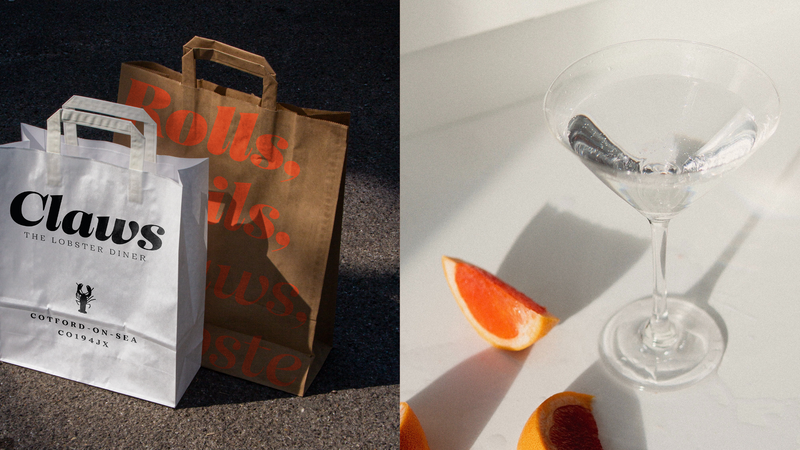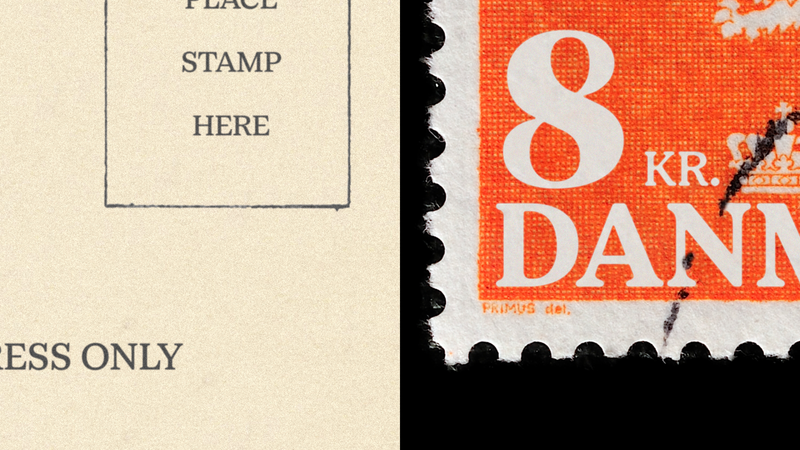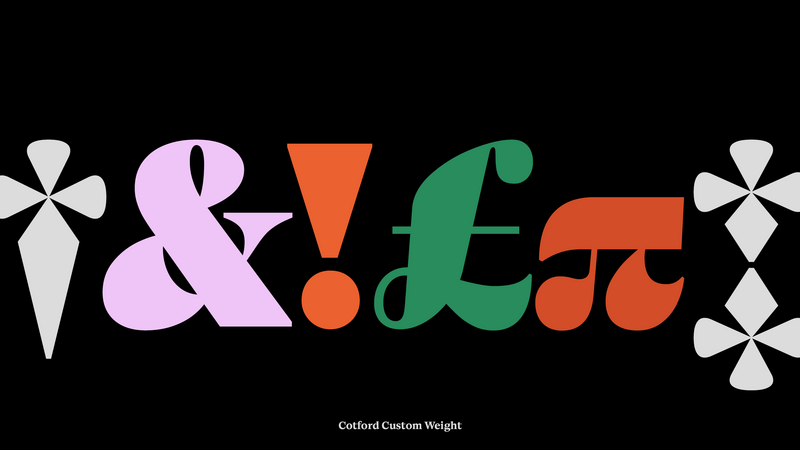
El pasado siempre vuelve: Análisis en profundidad de la nostalgia en el diseño
La nostalgia, que se cree que ayuda a las personas a sobrellevar las crisis, está más presente que nunca en diseños de todo tipo. Exploramos los factores que apuntalan esta tendencia y algunas de las dificultades inherentes al resurgimiento de elementos de diseño históricos.
En los últimos dos años, la nostalgia ha empezado a colarse en muchas facetas de nuestra vida cotidiana: la moda, el mobiliario, las identidades de marca e incluso la música que escuchamos en línea. En lo que han sido los dos años más inciertos e inestables de la vida de la mayoría de la gente, tanto marcas como profesionales del diseño han tratado de transmitir una sensación de alivio a través de diseños que nos resultan familiares. Se trata de una estrategia que tiene sentido a nivel científico, ya que según algunos estudios de psicología, rememorar tiempos pasados puede ayudar a las personas a sobrellevar las crisis.
Al igual que quienes adoran comprar antigüedades, a los y las profesionales del diseño les encanta inspirarse en logotipos, libros y carteles antiguos, y rendir homenaje a esos diseños. ¿Cuántos tipos de letras se habrán inspirado en la tipografía de un libro antiguo descubierto en una librería de segunda mano o en una postal encontrada en un mercadillo? Es una forma de rendir homenaje a los clásicos o de preservar un estilo único, ya sea en un logo, en el armario o en el hogar.
Incluso el lanzamiento más reciente de Monotype Studio, un tipo de letra moderna con remate llamada Cotford, obra del director creativo de tipografía Tom Foley, tiene ese toque nostálgico. «Cotford plasma la sensación que muchas personas experimentamos durante el punto álgido de los confinamientos del año pasado: el anhelo por la comodidad de lo conocido y por un poco de calidez en medio de la tormenta».
“
¿Cómo recuperamos elementos de diseño divertidos y reconfortantes del pasado sin ignorar las verdades más dolorosas de cada época? ”
Cottord, de Monotype Studio.
La emoción del hallazgo.
Más allá de la tipografía y el diseño gráfico, los estilos vintage han ganado popularidad en el sector del mobiliario, la decoración del hogar y la moda. El ritual de descubrir una reliquia excepcional y darle una nueva vida en el mundo moderno ha ofrecido algo de consuelo durante la pandemia y ha adquirido popularidad en nuevos canales, como Instagram, así como en sitios web de moda de segunda mano, como Depop.
En la moda, las tendencias siempre han sido cíclicas. Sin embargo, según ThredUp, una tienda de reventa en línea, la compra de artículos de segunda mano se ha convertido recientemente en un sector que mueve 36 000 millones de dólares y que se espera que eclipse a la moda rápida en 2025. La mayor importancia que dan a la sostenibilidad muchos consumidores y consumidoras jóvenes hace que se decanten por estas opciones en lugar de seguir contribuyendo a la moda rápida. Además, la pandemia ha generado problemas en las cadenas de suministro de prácticamente todos los sectores. Ante esta situación, parte de la clientela prefiere disfrutar de la recompensa instantánea que le ofrece comprar artículos de segunda mano y no tener que esperar para recibir artículos nuevos.
La búsqueda de tesoros vintage también se produce fuera del mundo digital, tal como Tyler Haughey, fotógrafo, explicó en nuestro pódcast. El trabajo de Tyler consiste en explorar la forma en que determinados significantes, como las señales o los elementos decorativos antiguos, nos ayudan a fijar recuerdos o afianzar experiencias. «Los recuerdos empiezan siendo muy vívidos, frescos y tangibles», explicó Haughey, «pero, a medida que pasa el tiempo, se vuelven más bien raros y adquieren un cierto aire de fantasía. Creo que en la naturaleza intrínseca de la memoria está el volverse menos específica con el paso del tiempo».
Todos estos elementos, ya sean fuentes alegres propias de los años setenta, fotos borrosas de antiguas ciudades costeras, vaqueros desgastados o muebles antiguos, nos permiten revivir el pasado y narrar nuestra historia. En nuestro Informe de tendencias de 2021, identificamos por primera vez una tendencia en versión suave al uso de fuentes serif tras observar la aparición de fuentes con remate clásicas, reconfortantes y muy nostálgicas, con influencia de Cooper Black, en las renovaciones de marca de Chobani (InHouse), MailChimp (Collins), Meridian (BulletProof), Dunkin y Burger King (JKR). Después de un año implacable, la tendencia se ha consolidado, materializándose en formas de letras con florituras joviales, remates gruesos, letras extravagantes y esquemas de colores vibrantes.
Homenaje a la diversidad en la historia.
Sin embargo, en este resurgir histórico, nos topamos con un aspecto peliagudo: diferenciar entre la admiración por elementos de diseño históricos y los contextos sociales poco favorables en los que se crearon muchos de ellos. «Todo este movimiento nostálgico que enaltece lo antiguo puede llevarnos a ignorar cuestiones tan importantes como el sexismo, el racismo o la desigualdad social y mostrarnos conformistas con estas desigualdades», apuntó Charles Nix, director creativo de Monotype, en una entrevista de Print Mag sobre la reaparición de equipaciones deportivas retro.
“ ¿Cómo recuperamos elementos de diseño divertidos y reconfortantes del pasado sin ignorar las verdades más dolorosas de cada época? ”
Para analizarlo desde el ámbito de la tipografía, analizaremos el trabajo que Tré Seals, propietario y fundador de Vocal Type, está haciendo para utilizar las fuentes como medio para contar historias. Todos los tipos de letra de Vocal Type tienen su origen en acontecimientos históricos, como manifestaciones y protestas, y llevan el nombre de destacados defensores y defensoras de la justicia social, como Marsha P. Johnson, Martin Luther King o Bayard Rustin.